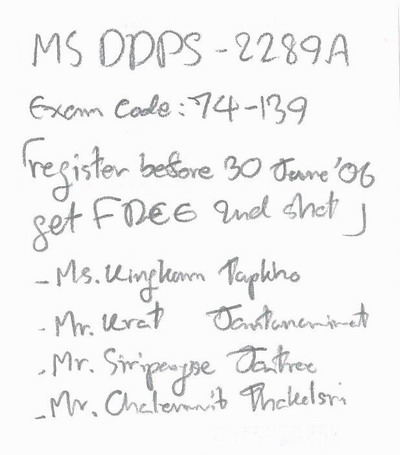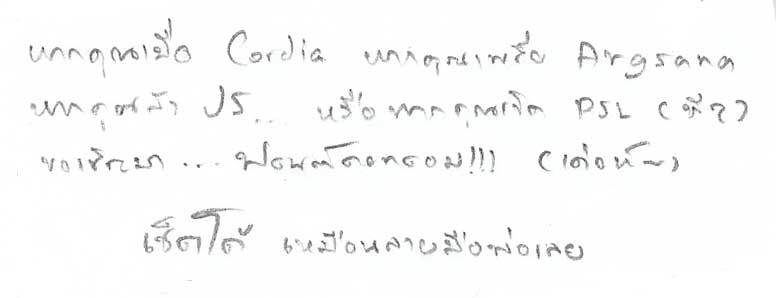
กระจู๋โชว์ลายมือ
อิจฉา  :05:
(เดี๋ยวพรุ่งนี้จะสแกนลายมือมาให้ดู พอๆกะเคนเลย  :31:)
เด็กเซนต์โยลายมือน่ารักเยอะมาก
(แต่ยกเว้นวี :03:)
ลายมือ (?) จาก memo ทั้งหมดใช้เวลาไม่ถึง 10 วินาที
ระวังตาบอด :31:
ลายมือพี่อย่างห่วยเลย  :05:
ก็ใจร้อน รีบเขียนนี่ :05:
ลายมือไม่สวยเพราะไม่ค่อยได้เขียน
ส่วนมากจะพิมพ์
แล็กเชอร์ก็ไม่จด ใช้ซีร็อกจากเพื่อนเอา  :03:
พอจะเขียนทีมือมันแข็ง เขียนไม่ออก
อยากเขียนลายมือแบบนี้ได้อะ  :25:
พีชเขียนไม่ได้ เขียนเร็วๆทีไรแล้วมันต้องอ่านไม่ออก
แบบเหมือนมันไม่ได้เขียน แต่มือมันกระตุกไปเอง  :08:
ตูอ่านได้แต่ ฟอนต์ดอทคอม  :08:
ลายมือเหมือนผู้ใหญ่เลย สาม  :42:
แต่อ่านบรรทัดที่สองไม่ออก  :08:
วันนี้จดตามครูพูด  เร็วอย่างกับจรวด  :08:
ลายมือแรกๆก็ดีหรอก ไปๆมาๆ ชักเละ
สุดท้าย .. เขียนไม่ทัน รอลอกเพื่อนอย่างเดิม  :08:
เดี๋ยววันจันทร์จะเอามาโชว์ ตอนนี้ใบนั้นอยู่โรงเรียน  :42:
:05:นานาอ่านออกหมดนะ
หรือลายมือนานาจะ......
(ลองเขียนดูแล้ว อ่านยากจริงๆด้วย เดี๋ยวไปสแกนสมุดมาดโชวืดีกว่า)
แบบจดเอา (ไม่ค่อยรีบ)
ในวิชาการงาน
อยากอ่านแบบแลคเชอร์อะดิ :26:
ไม่แปลกหรอกที่จะ่อานไม่ออก บางทีนานาก็อ่านไม่ออกเหมือนกัน (ของสามกะเคนนี่อ่านง่ายมากๆเลยนะสำหรับนานา *-*)